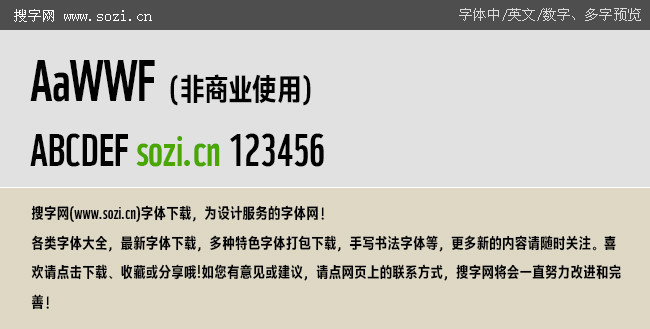
AaWWF
搜字網(wǎng)給大家提供一款A(yù)aWWF(非商業(yè)使用)中文字體下載,該字體是一款黑體中文字體,字體瘦長且醒目,簡潔大方,適合書裝設(shè)計(jì)、包裝設(shè)計(jì)、海報(bào)設(shè)計(jì)等應(yīng)用(此字體為個(gè)人非商用版,商用可以聯(lián)系QQ:1006760504)。